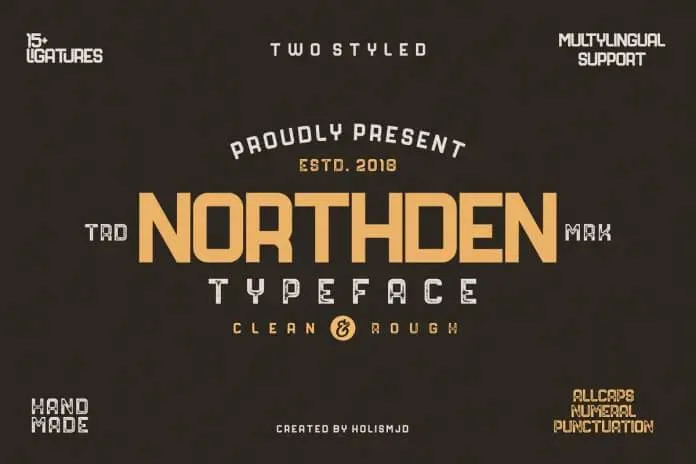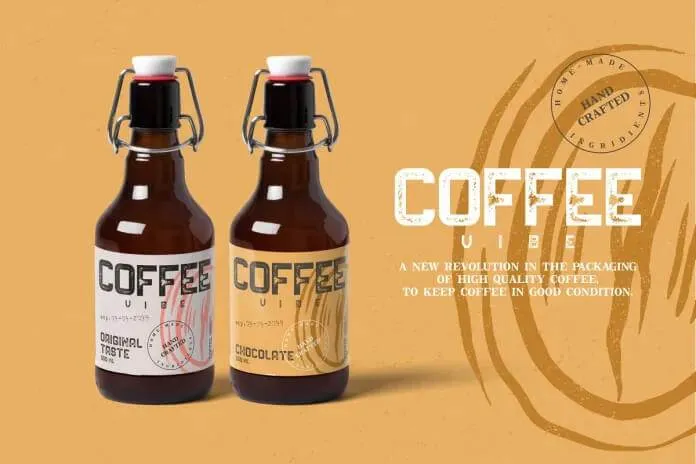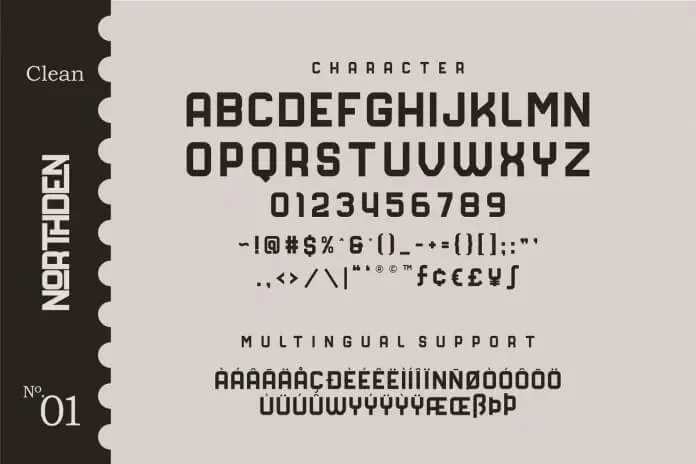
Font Northden – Tải font chữ phong cách nam tính miễn phí
Font Northden là font chữ Industrial typeface với phong cách nam tính phù hợp với nhu cầu thiết kế của các bạn cần nét cổ điển, vintage nhưng vẫn hiện đại. Phông chữ này là hoàn hảo, cho bất kỳ logo, nhãn sản phẩm, áp phích hoặc thiết kế nào. Phông chữ này có 2 kiểu, sạch và thô.
Đặc trưng font:
• Tất cả chữ hoa
• Dấu câu & Số
• Hơn 15 chữ ghép
• Hỗ trợ đa ngôn ngữ ÀÁÂÃÄÅÆÇÈÉÊËÌÍÎÏÑÒÓÔÕÖØÙÚÛÜÝ